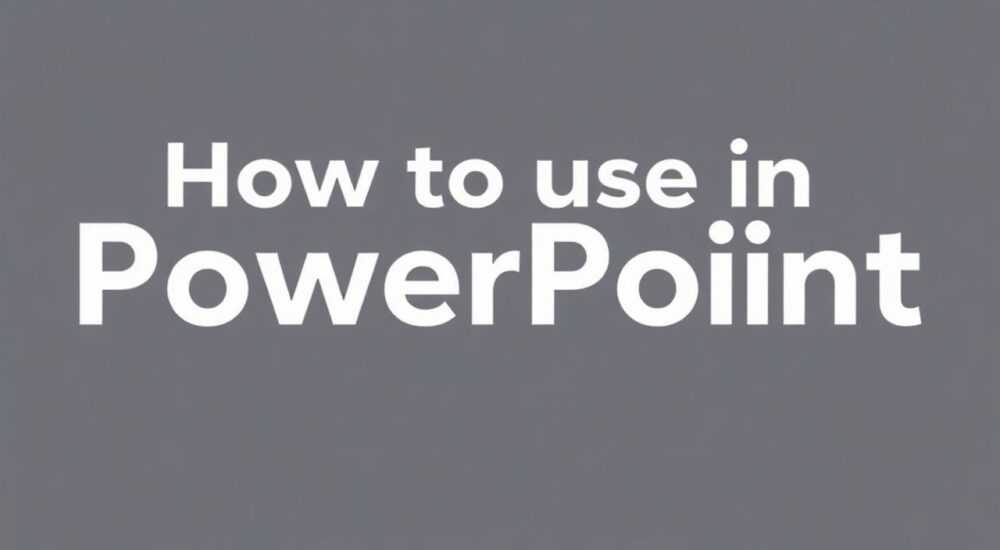
Как использовать шрифты в повер поинт
Качественные шрифты в PowerPoint — это не просто элемент оформления, а мощный инструмент воздействия на восприятие информации. Они влияют на читаемость, эмоциональный отклик и общее впечатление от презентации. Неправильный выбор может свести на нет даже самое сильное содержание.
Сегодня, когда презентации демонстрируются как в конференц-залах, так и на экранах смартфонов, грамотное применение шрифтов становится критически важным. От них зависит, запомнит ли аудитория ключевые тезисы или быстро потеряет интерес. В этой статье мы детально разберём, как выбирать, настраивать и использовать шрифты в PowerPoint, чтобы сделать ваши слайды профессиональными, понятными и визуально привлекательными.
Основы типографики в PowerPoint
PowerPoint предлагает широкий выбор шрифтов, встроенных в операционную систему и офисный пакет. Однако важно понимать, что не все шрифты одинаково эффективны для презентаций. Типографика — это искусство расположения текста, обеспечивающее его читаемость и визуальную гармонию.
Шрифты делятся на несколько основных категорий: засечковые, беззасечковые, рукописные и декоративные. Засечковые (например, Times New Roman) хорошо читаются в печати, но могут теряться на экране при маленьком размере. Беззасечковые (Arial, Calibri, Helvetica) — оптимальный выбор для цифровых презентаций благодаря чёткому контуру.
Размер шрифта играет решающую роль. Рекомендуется использовать минимум 24 пункта для основного текста, а заголовки — от 32 до 44 пунктов. Это обеспечивает видимость даже в задних рядах зала. Межстрочный интервал также влияет на восприятие: увеличение на 10–15% делает текст легче для глаз.
Цвет текста должен контрастировать с фоном. Чёрный на белом или белый на тёмном — классическое решение. Избегайте светлых цветов на светлом фоне и слишком ярких комбинаций, которые вызывают усталость глаз.
Как изменить шрифт в PowerPoint
- Выделите текст на слайде с помощью мыши или клавиш Ctrl+A для выделения всего текста.
- Перейдите на вкладку «Главная» в верхнем меню.
- В группе «Шрифт» выберите нужный шрифт из выпадающего списка.
- Настройте размер, цвет, начертание (жирный, курсив) и межстрочный интервал.
Для массового изменения шрифтов по всей презентации используйте функцию «Замена шрифтов»: вкладка «Главная» → «Редактирование» → «Заменить» → «Заменить шрифты». Это особенно полезно при адаптации презентации под корпоративный стиль.
Как выбрать подходящий шрифт
Выбор шрифта начинается с определения цели презентации. Деловой отчёт требует строгих, нейтральных шрифтов, тогда как креативная презентация допускает более свободный подход. Контекст использования — ключевой фактор.
Рассмотрим распространённые варианты:
- Calibri — шрифт по умолчанию в современных версиях PowerPoint. Универсален, современный, отлично читается на экране.
- Arial — беззасечковый шрифт с высокой универсальностью. Подходит для технических и деловых презентаций.
- Segoe UI — разработан Microsoft для интерфейсов. Чистый, лёгкий, идеален для цифровых демонстраций.
- Times New Roman — засечковый, традиционный. Лучше подходит для документов, чем для слайдов.
- Montserrat, Lato, Open Sans — популярные бесплатные Google Fonts, часто используются в дизайне презентаций.
Когда какой шрифт использовать
Тип презентации |
Рекомендуемый шрифт |
Почему подходит |
Бизнес-встреча |
Calibri, Arial |
Нейтральные, профессиональные, легко читаются |
Креативный брифинг |
Montserrat, Raleway |
Современные, с характером, привлекают внимание |
Академическая защита |
Times New Roman, Georgia |
Традиционные, внушают доверие |
Онлайн-курс |
Open Sans, Roboto |
Отличная читаемость на малых экранах |